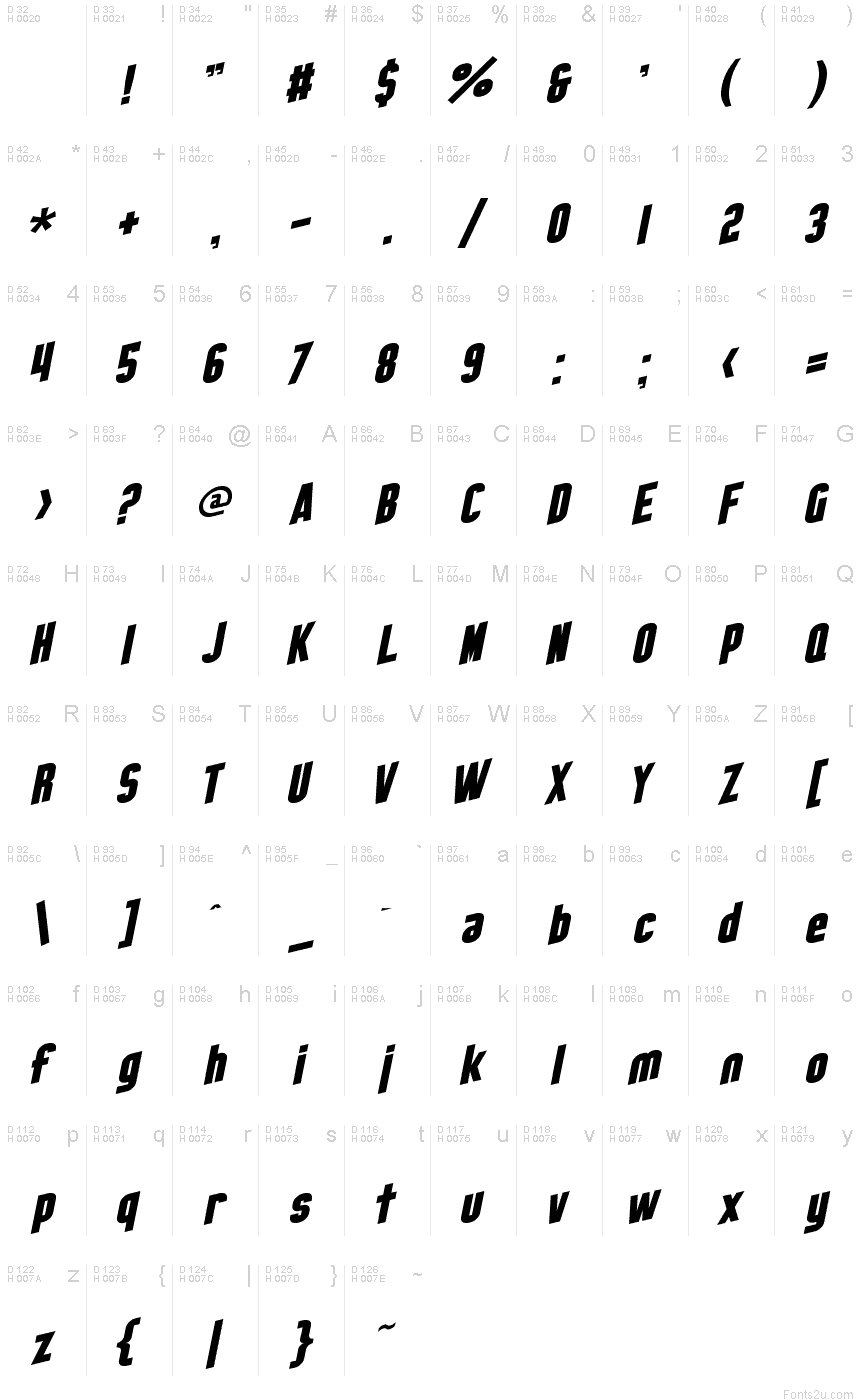
SF Obliquities od ShyFoundry to bezpłatny krój bezszeryfowy, oparty na dynamicznym nachyleniu i grubych, zwarcie ciętych literach. Font jest szybki i skondensowany, ale nieprzekombinowany; szerokie kreski, ostre kąty i lekko industrialny styl nadają mu mocny, zdecydowany wyraz.
Świetnie sprawdza się w brandingu sportowym, nagłówkach plakatów, tytułach gier, grafikach eventowych i śmiałych hasłach, gdzie krótkie słowa potrzebują raczej ruchu niż wygładzenia. Jako darmowy font, dobrze radzi sobie również w napisach na planszach i szkicach logo, ponieważ agresywne pochylenie i gęste kształty nadają wyrazistości nawet krótkim frazom.
SF Obliquities
ShyFoundry: SF Obliquities: 2008
ShyFoundry
Derek Vogelpohl